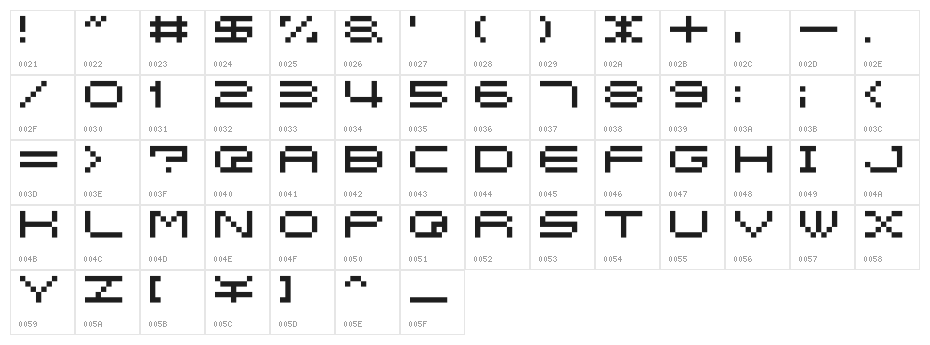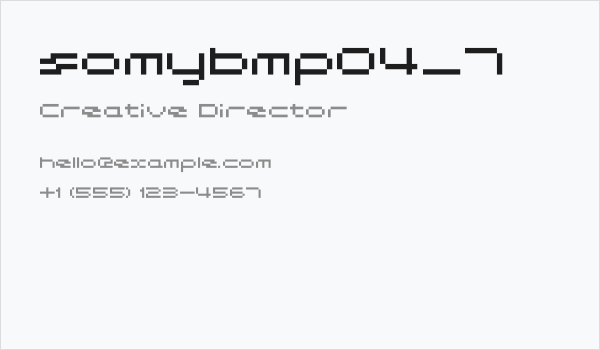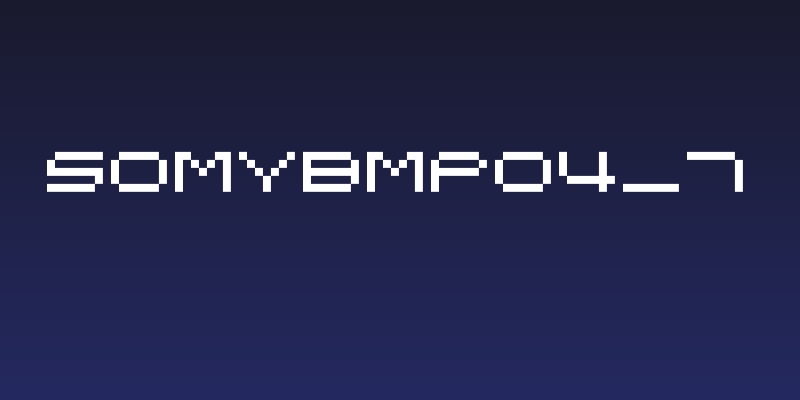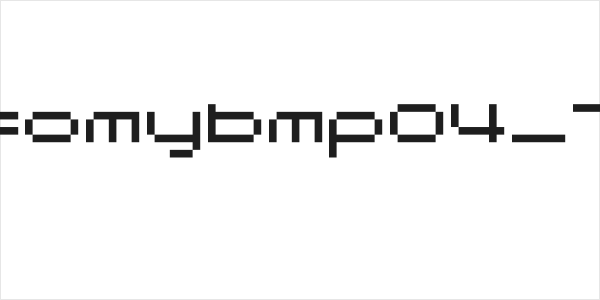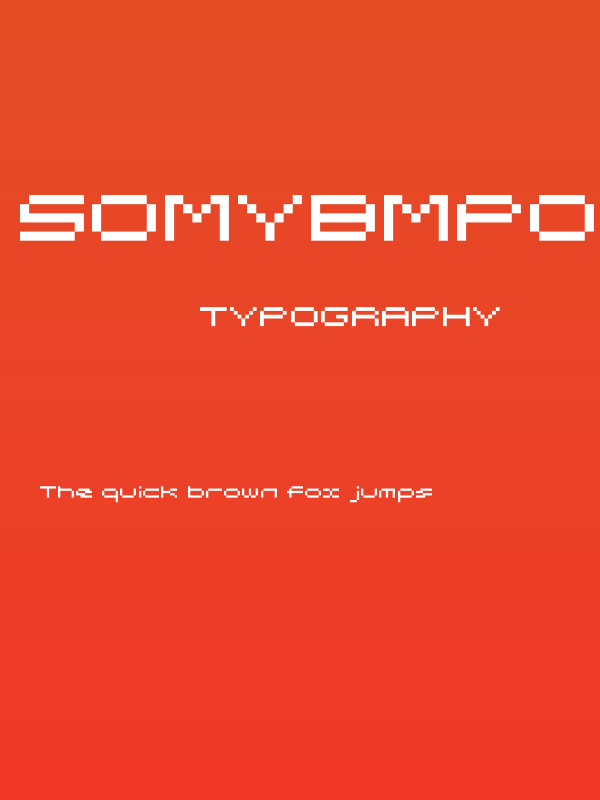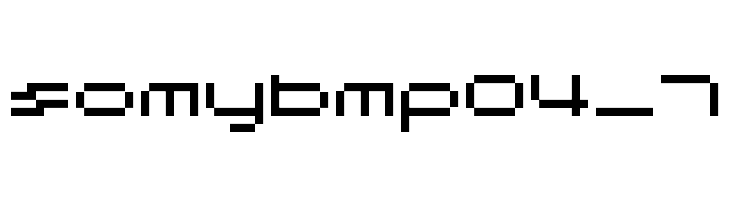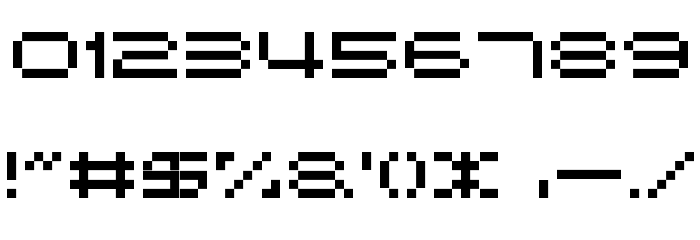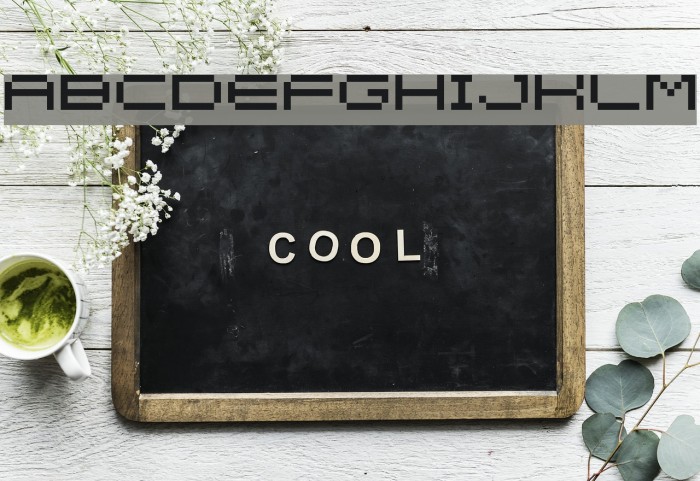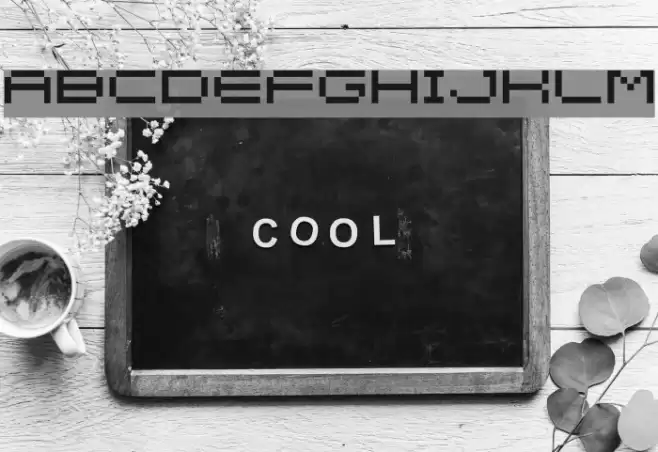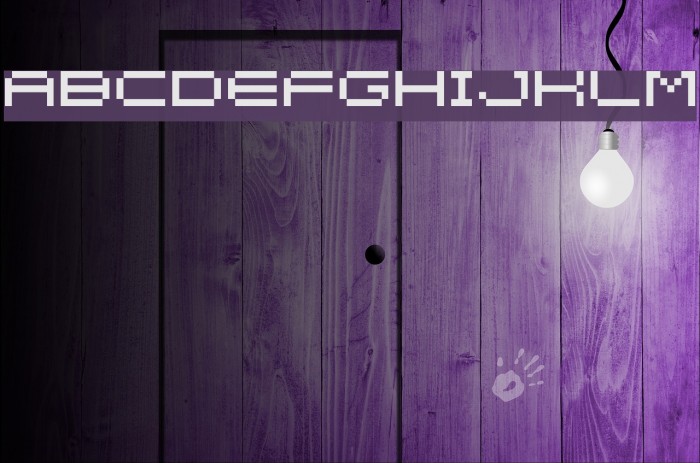
somybmp04_7 Font
| Stile generale | Retro, Digital |
| Caso d'uso | Logos, Digital displays, Video game text |
| Progetti proposti | Ideal for retro-themed video games, digital art projects, and designs that require a nostalgic or tech-inspired look. |